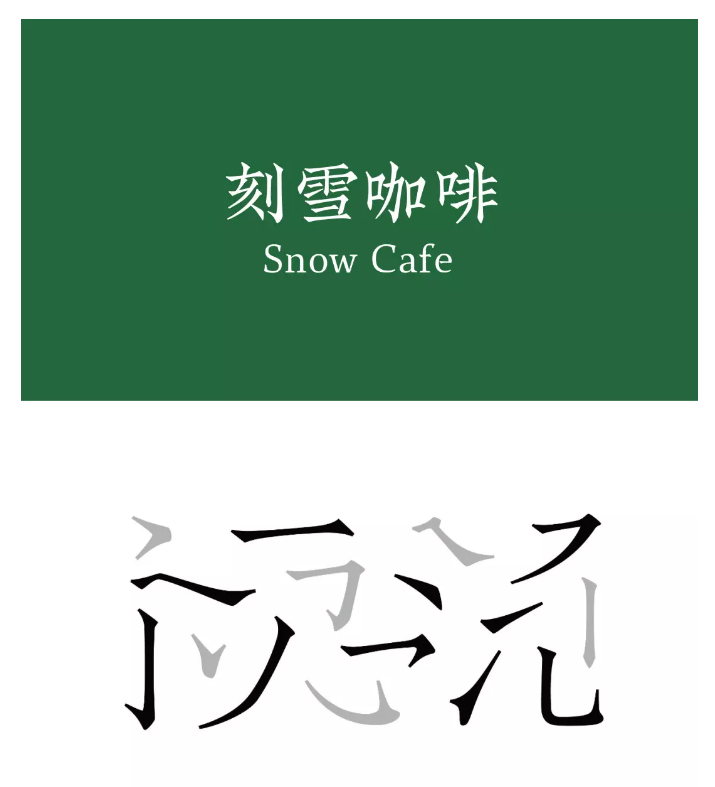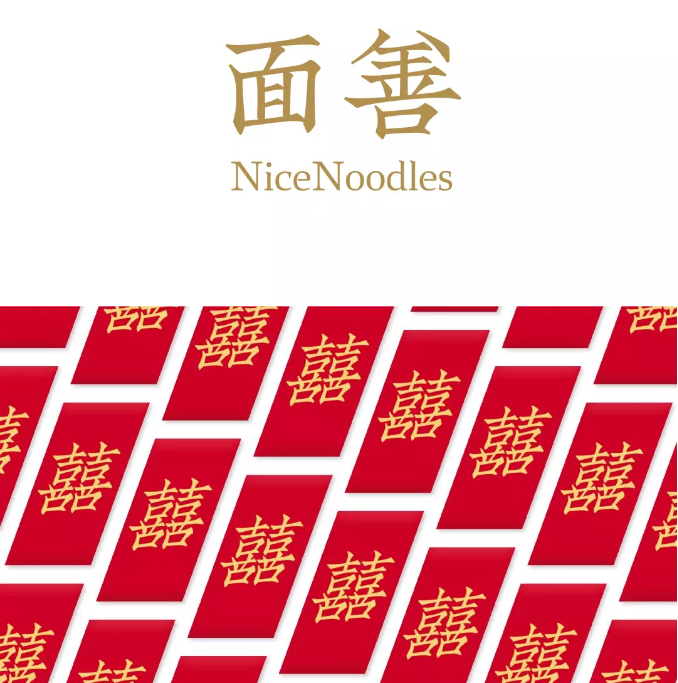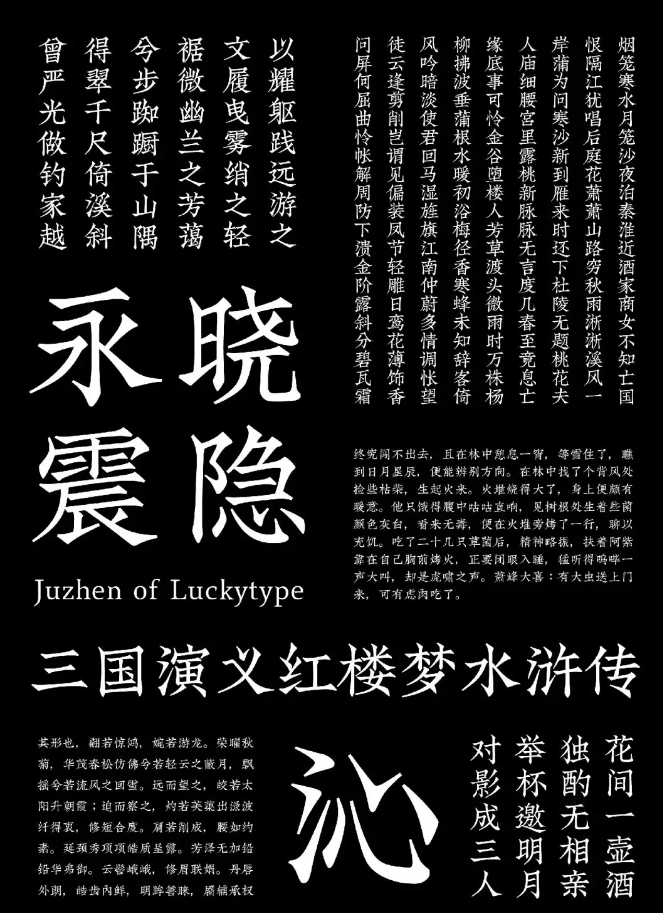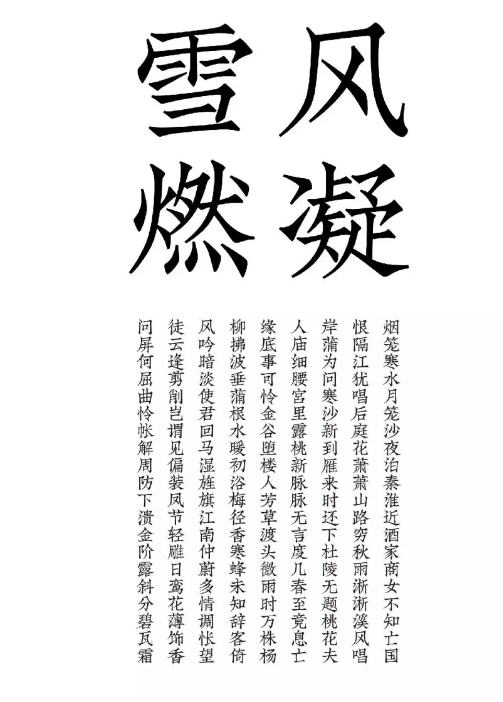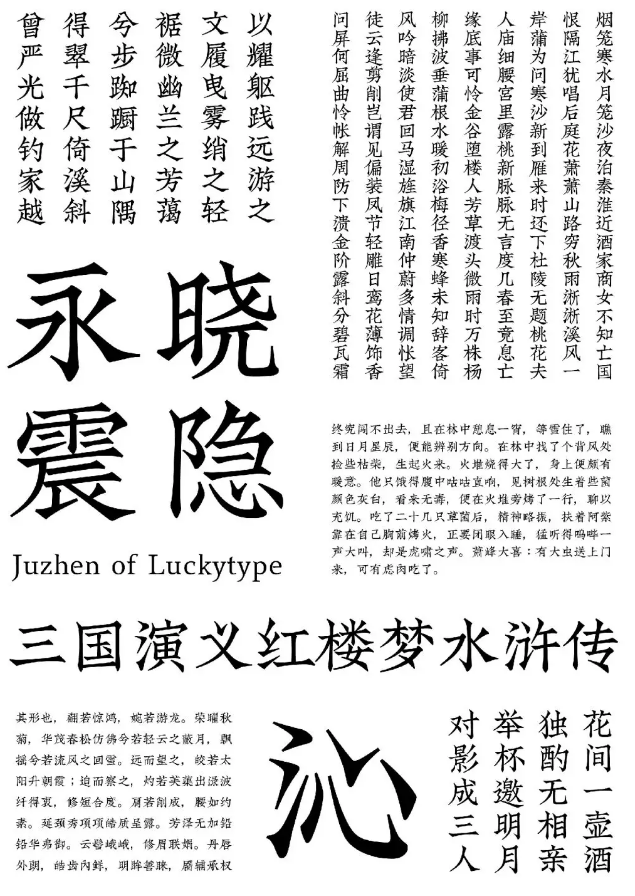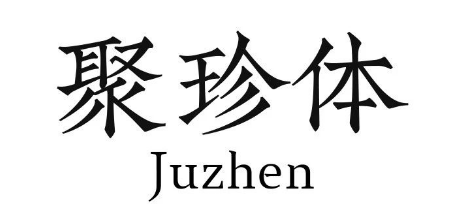
Font name:喜鹊造字聚珍体
喜鹊造字聚珍体,今天终于发布了,和约定的时间晚了一个月,俗话说好字不怕晚,让我们看看这次发布的喜鹊造字聚珍体吧。
聚珍体,是汲取20世纪初期丁氏兄弟所创聚珍仿宋风格,复刻而成的简体字聚珍体。
适用于排版老清新风格的正文或标题字需求,如传统中式品牌,文化创意、古籍排版、影视字幕等。
符合GB 2312标准,共收录6763个简体汉字和配套风格的英文以及标点。